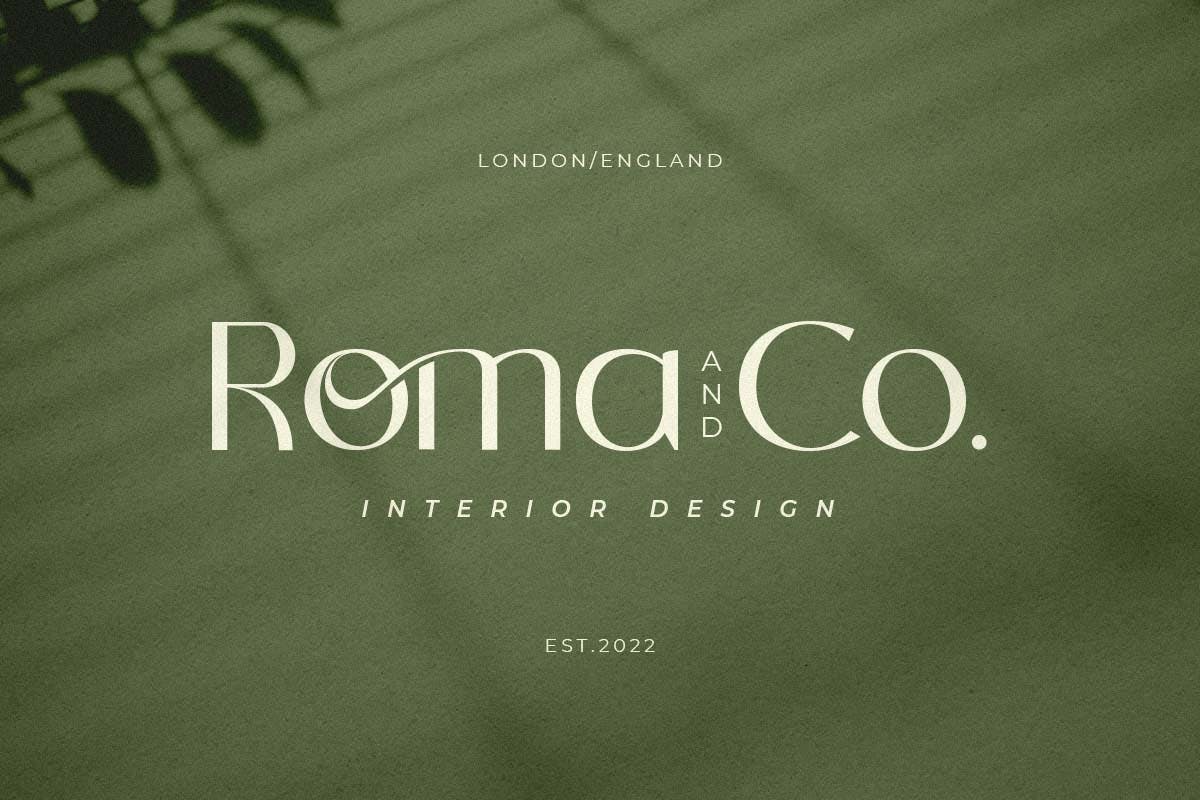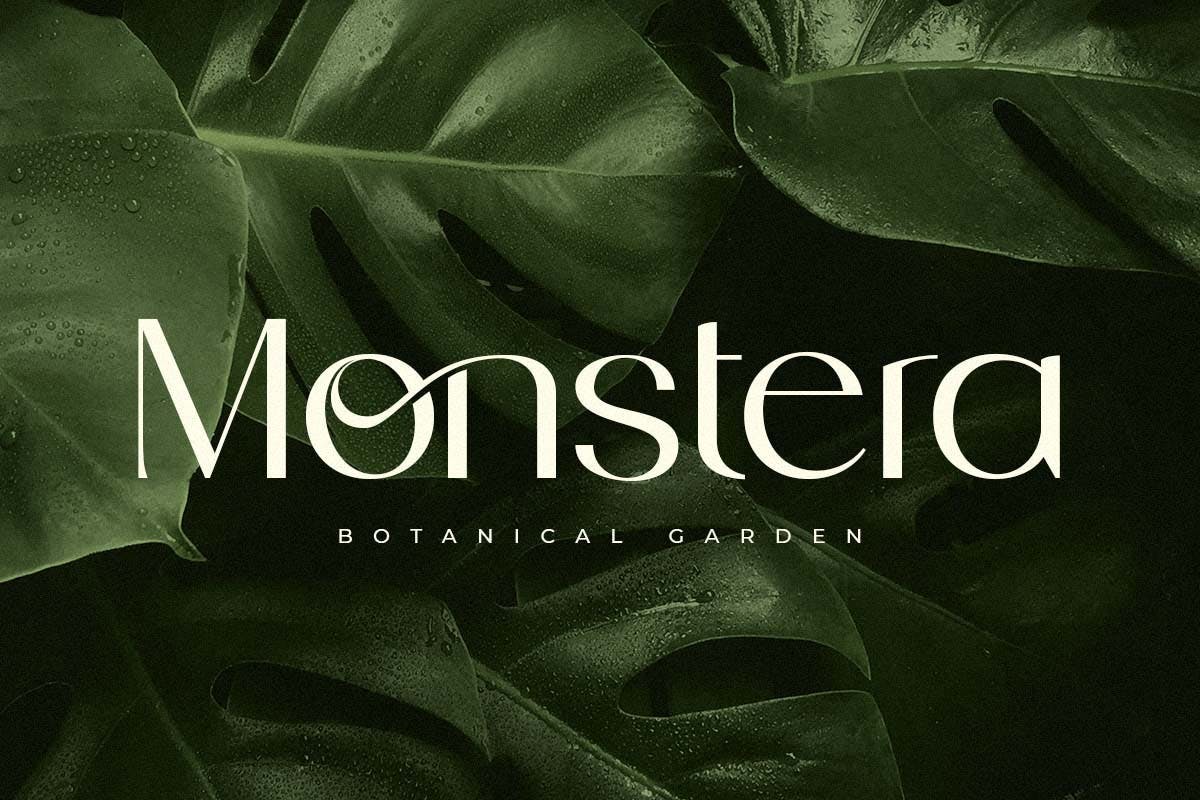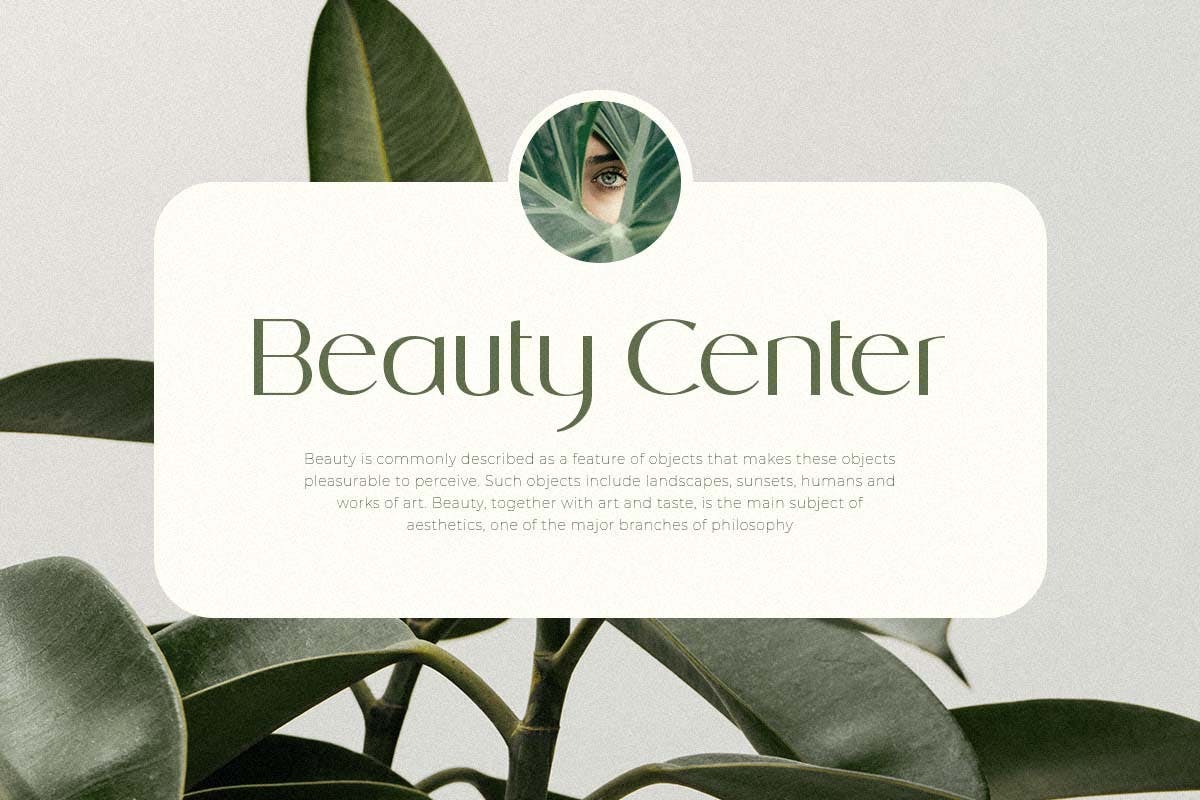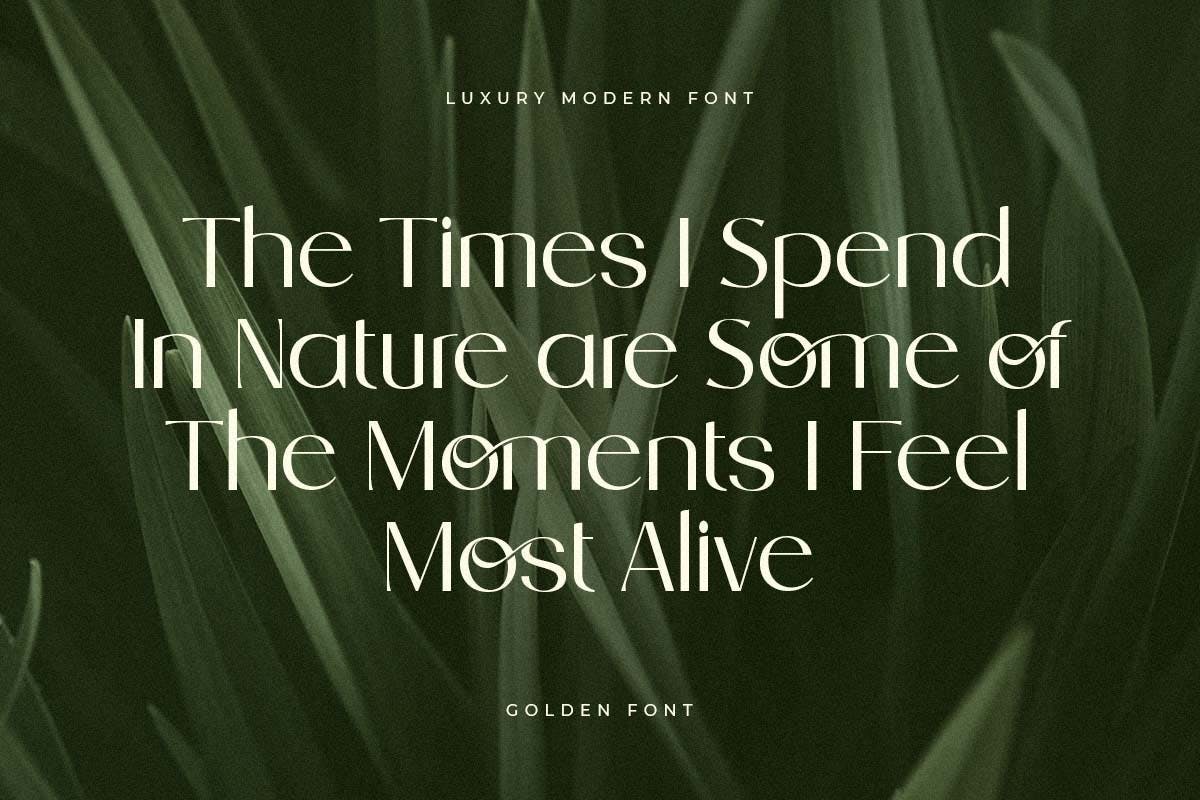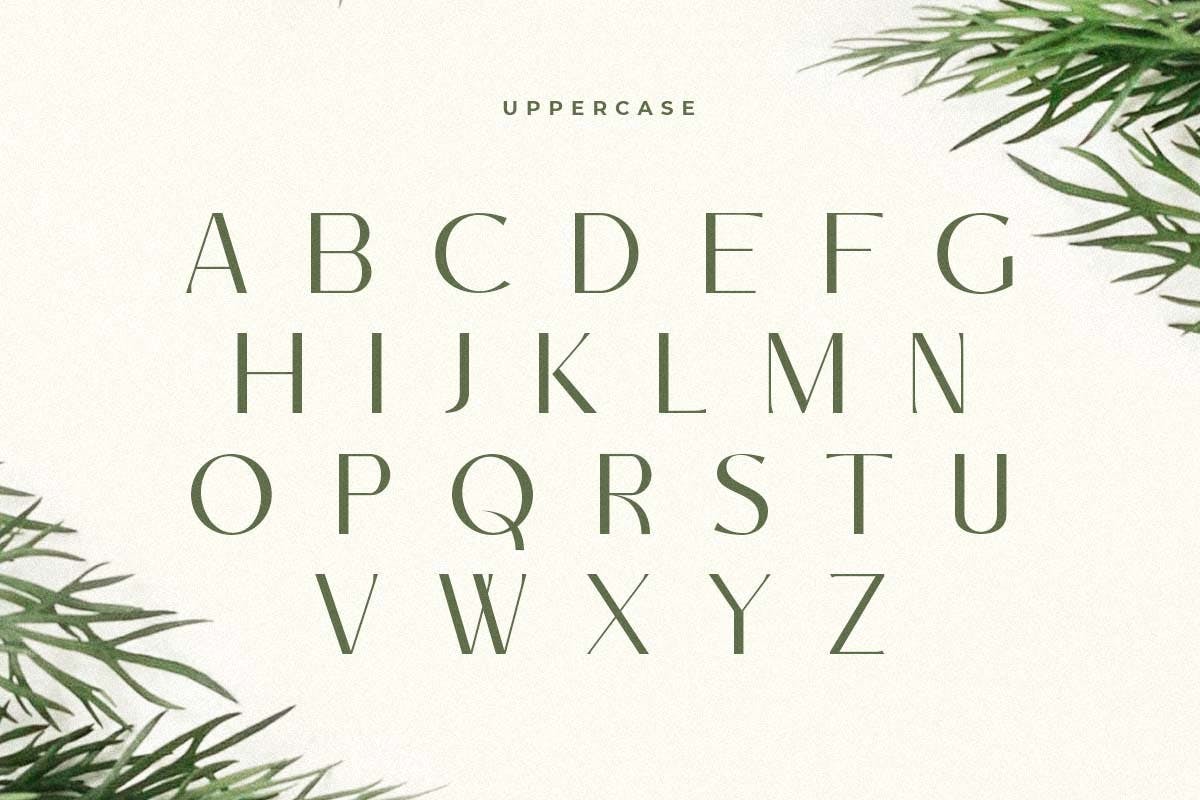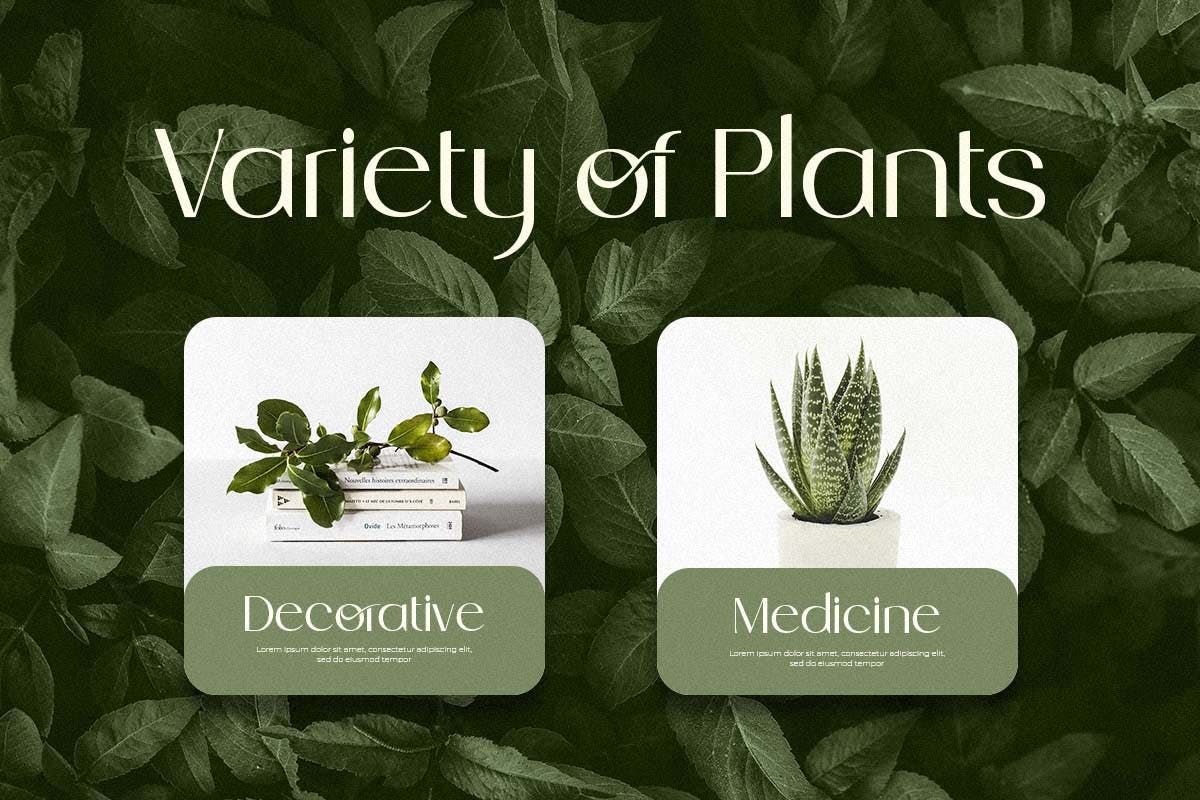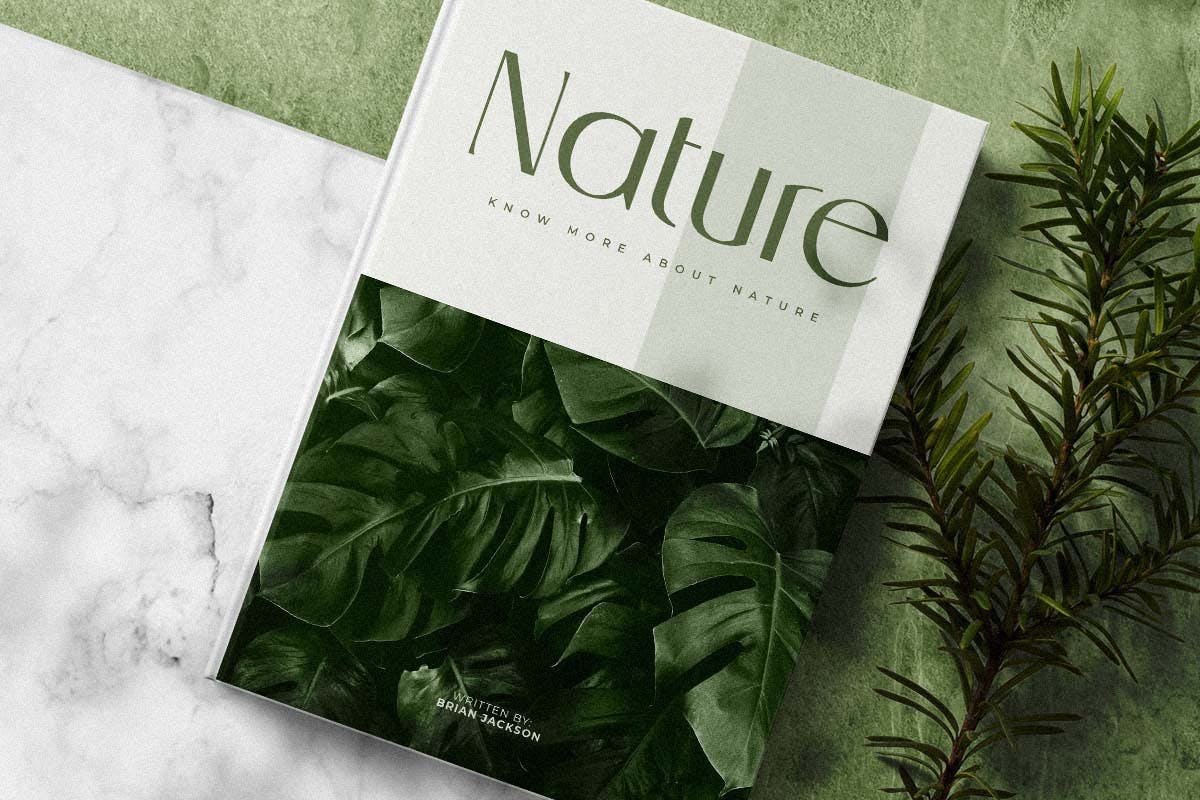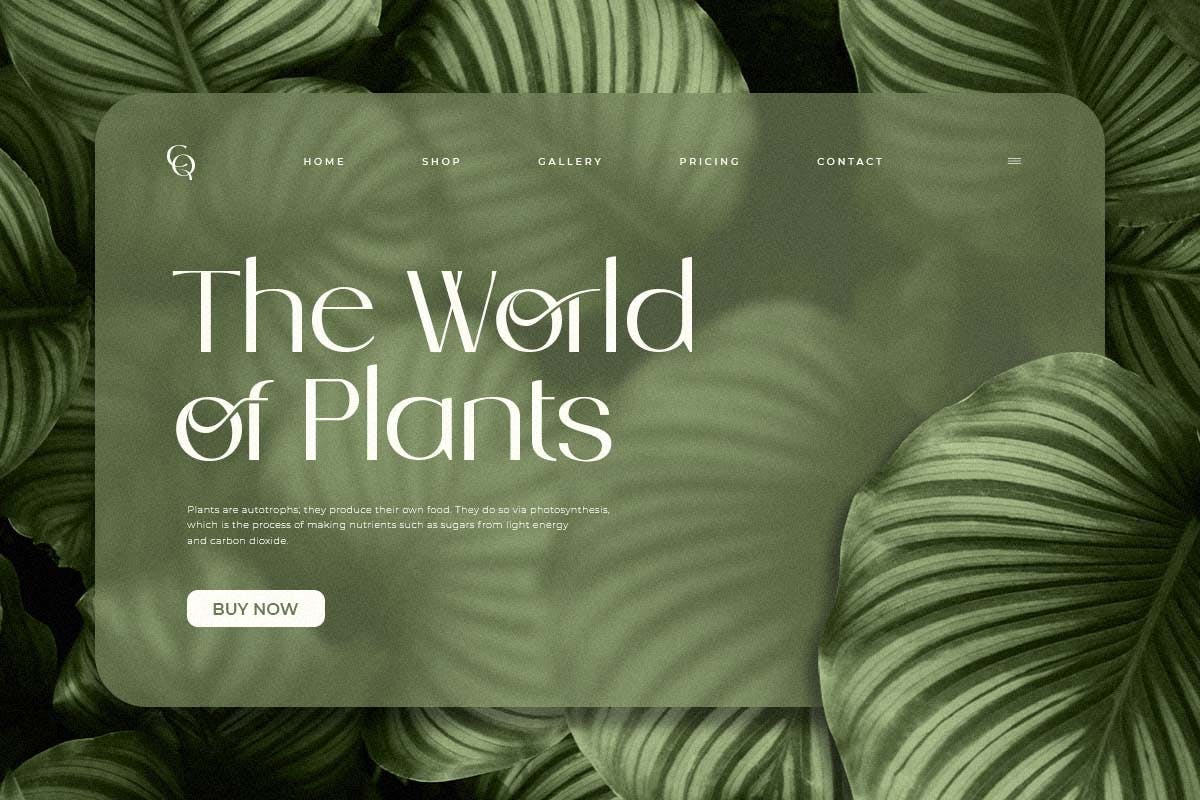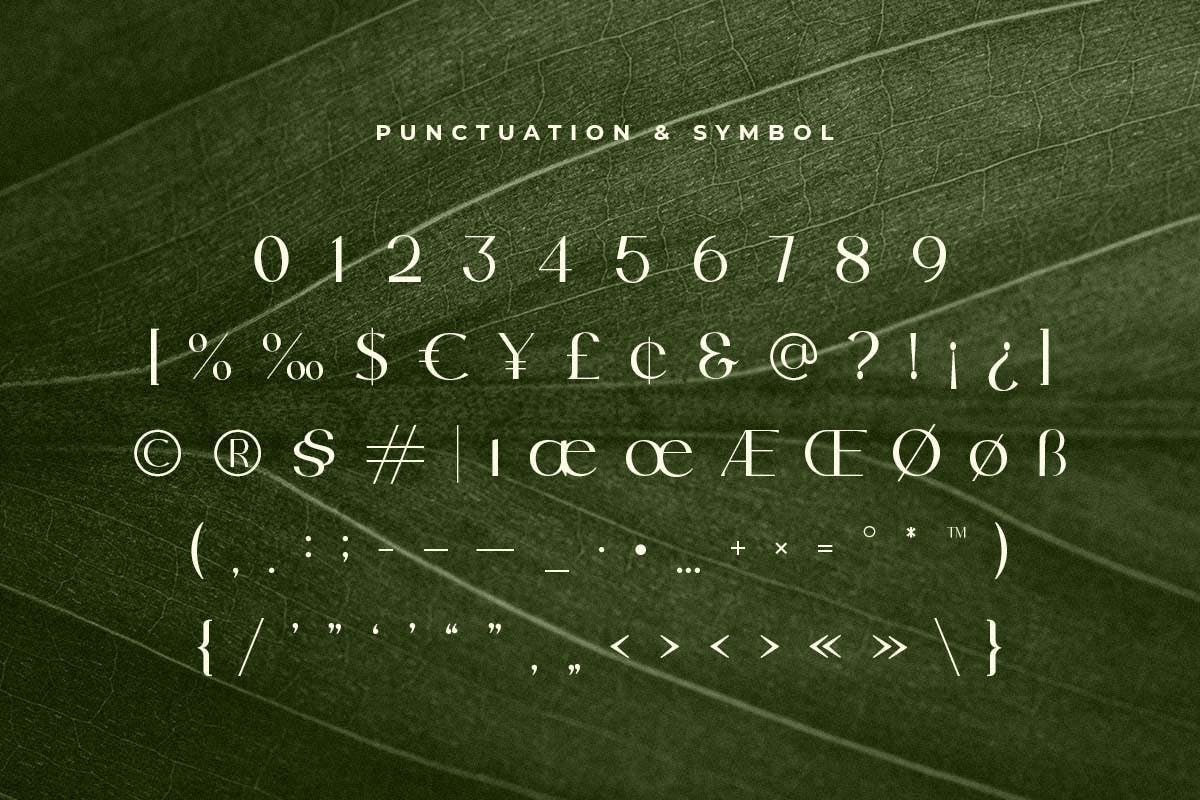
فونت Golden یک فونت مدرن لوکس و شیک با طراحی سنس سریف است که طراحی شما را کلاسیک و جذاب میکند.
این فونت سنس سریف جدید مخصوص عناوین، تیترها و نیازهای تایپوگرافی برجسته طراحی شده و با ویژگیهای اضافی خود، تنوعی خاص به پروژههای شما میبخشد. این فونت بهطور ویژه برای ایجاد سبک منحصر به فرد و حس مدرن طراحی شده است، بنابراین از خلق هر پروژهای که ایده اصلی شما را به نمایش میگذارد لذت ببرید.